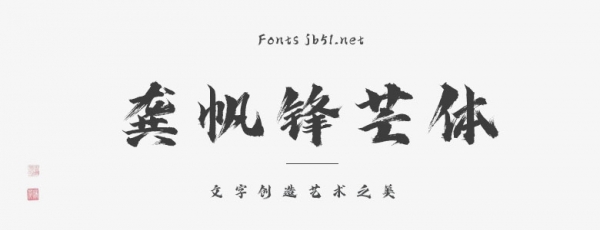
龔帆鋒芒體是一款非常磅礴大氣的書法藝術(shù)字體,字庫字?jǐn)?shù):6763常用簡體+常用字符+阿拉伯?dāng)?shù)字+英文字母大小寫,具有很好的視覺感,適合于文化類的宣傳設(shè)計(jì)、商業(yè)類品牌的廣告和產(chǎn)品包裝設(shè)計(jì)以及個(gè)性化文字排版等較多場景。
龔帆鋒芒體